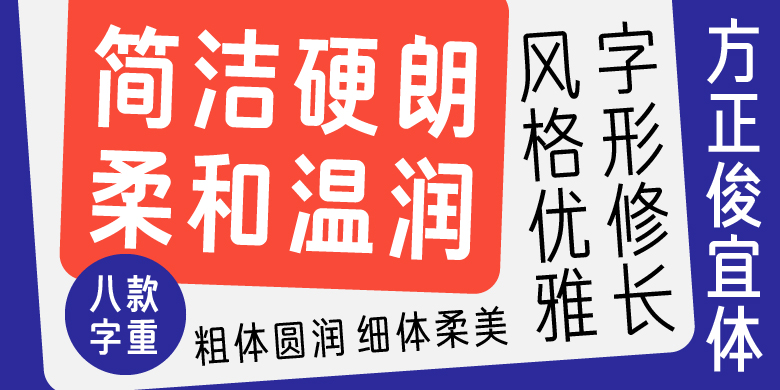
方正俊宜体家族
方正俊宜体家族,这款字体结构工整、笔画清晰,兼顾美观与易读性,适用于标题、正文、海报、包装、LOGO 等多种场景。字形优雅稳定,风格百搭耐看,适配日常排版与创意设计,让文字呈现更舒适、更具质感。方正俊宜体家族一笔一画,皆是细节,以均衡的比例、流畅的线条打造舒适视觉体验,字形端正大气,风格简约现代。无论是商业设计、品牌宣传还是日常排版,都能轻松驾驭,让文字更有格调与力量。方正俊宜体家族字体下载。
俊宜体家族是在方正俊黑家族基础上设计的,保留了俊黑体字形修长、风格优雅的特征。将笔画转折处做圆角处理,相较于俊黑体的简洁硬朗,俊宜体更显柔和温润,亲和感强。方正俊宜体家族共有8款不同字重,粗体圆润饱满、圆角特征明显,细体优雅柔美,是一套适用型强的家族字体,可应用于广告标语、包装设计、书刊出版、屏幕显示等。